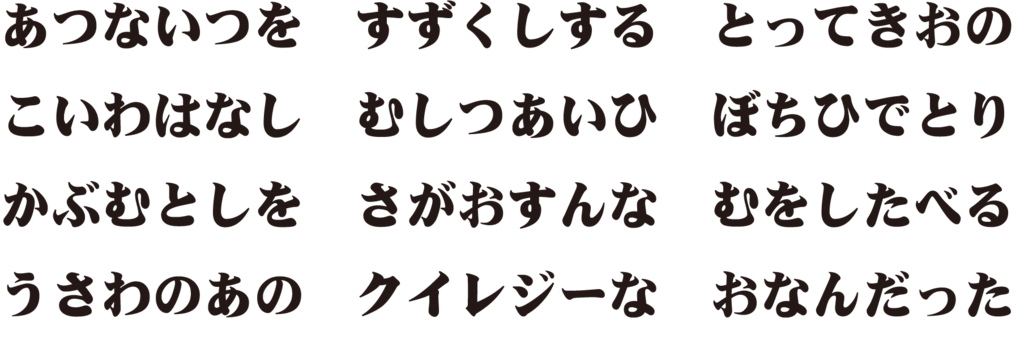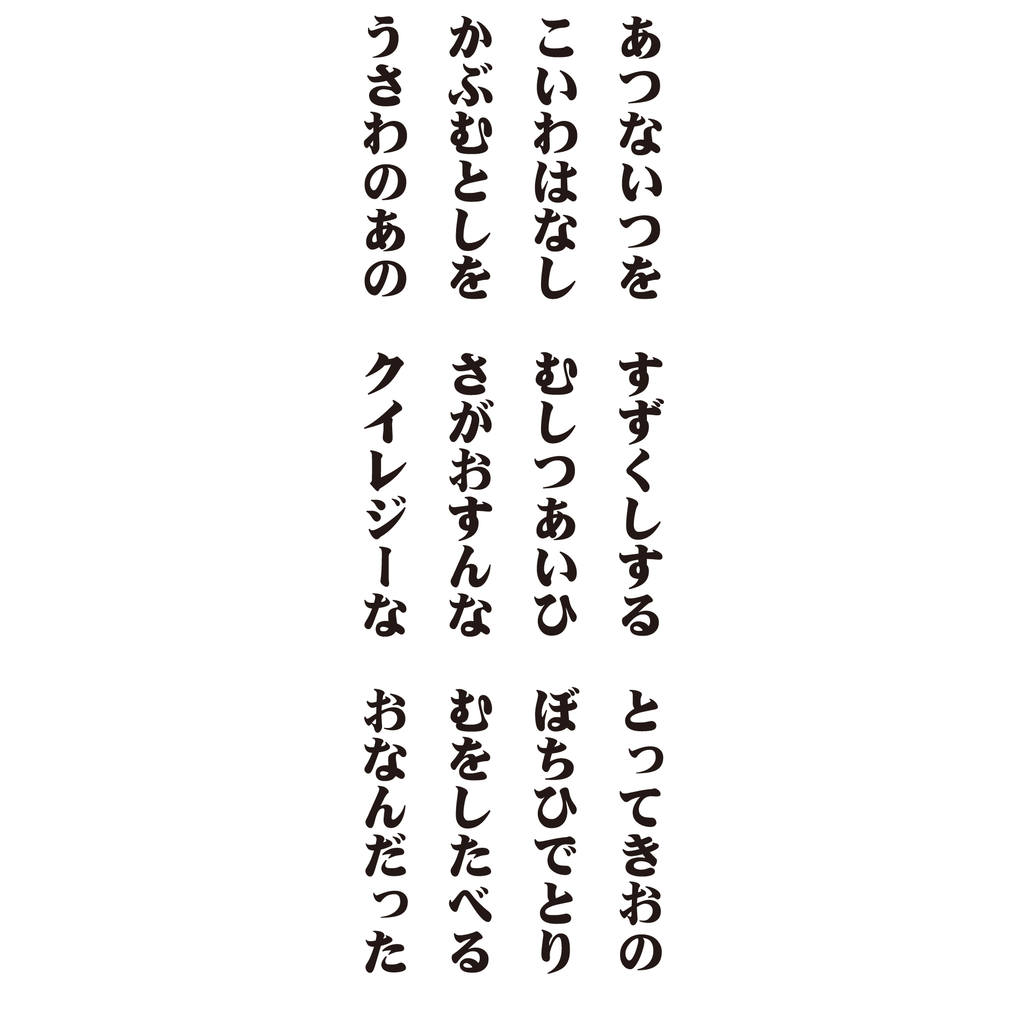
超極太明朝体を紹介
超極太明朝体は、華康明朝体をベースに通常のストロークの曲線や仮名の連画を増やし、横画においても三角形部分の円弧をより滑らかにデザインする事で、伝統的な書道の美しさを追求した明朝体。
極太より更に太い超極太なストロークの明朝体として、見出し部分や強調箇所にオススメ。
超極太明朝体と極太明朝体の太さを比較
ダイナフォントには極太明朝体というフォントもある。そこで超極太明朝体と太さを比較してみた。